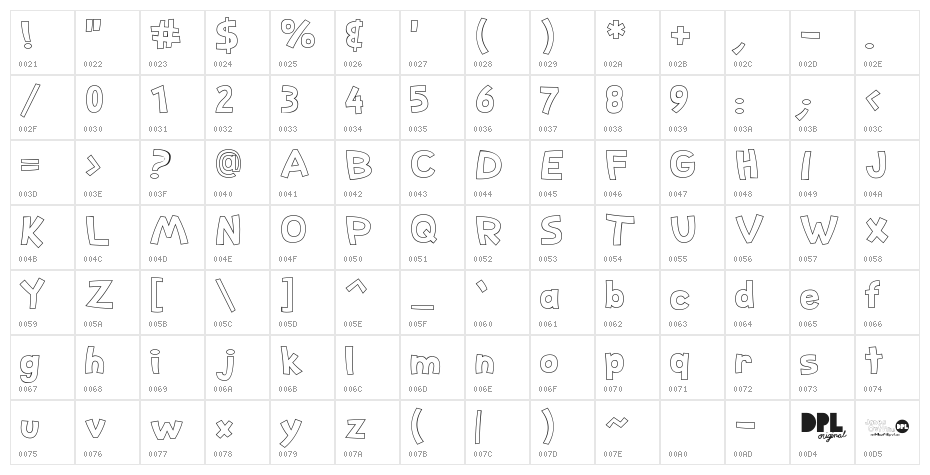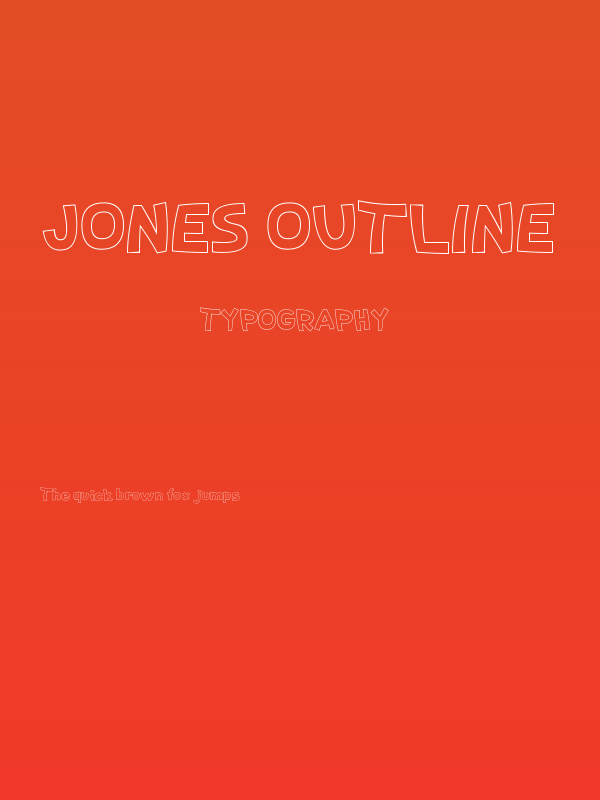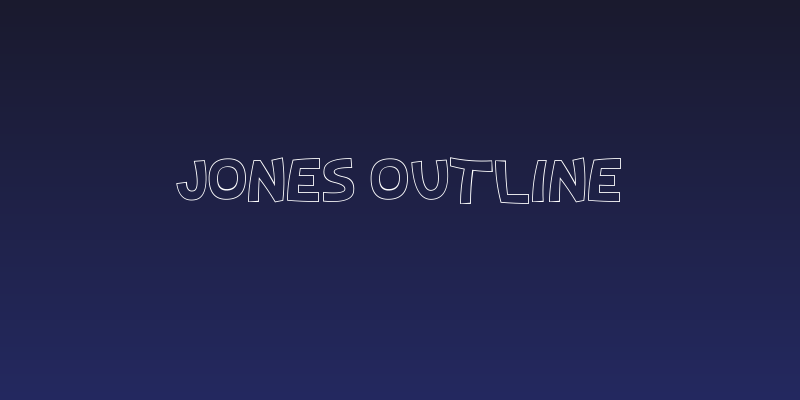
Jones Outline Font
| Stile generale | Playful, Fun, Whimsical |
| Caso d'uso | Headlines, Titles, Posters |
| Progetti proposti | Ideal for children's books, comic strips, playful branding, and creative posters. |